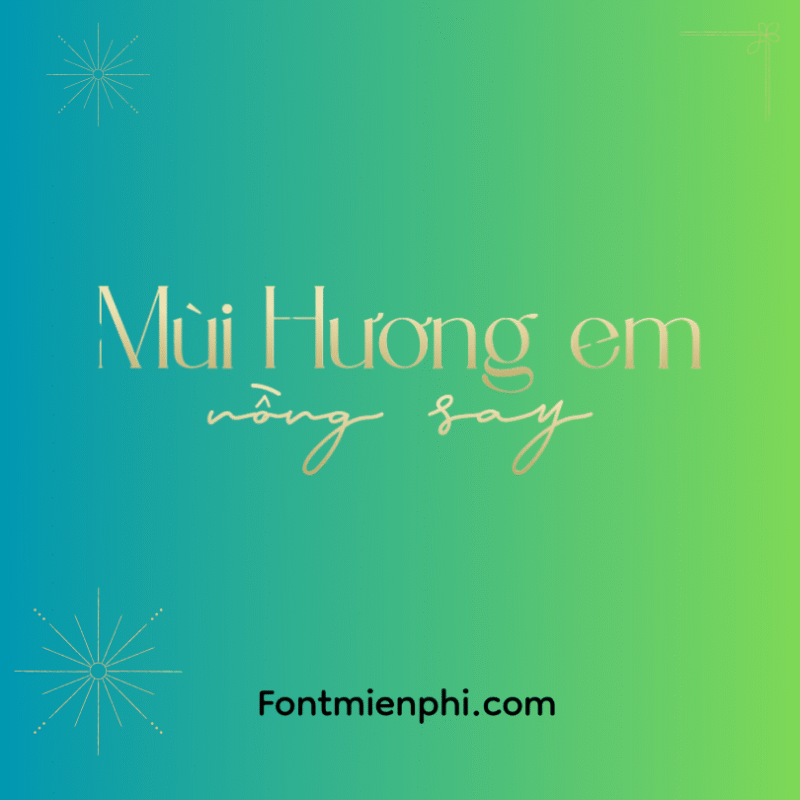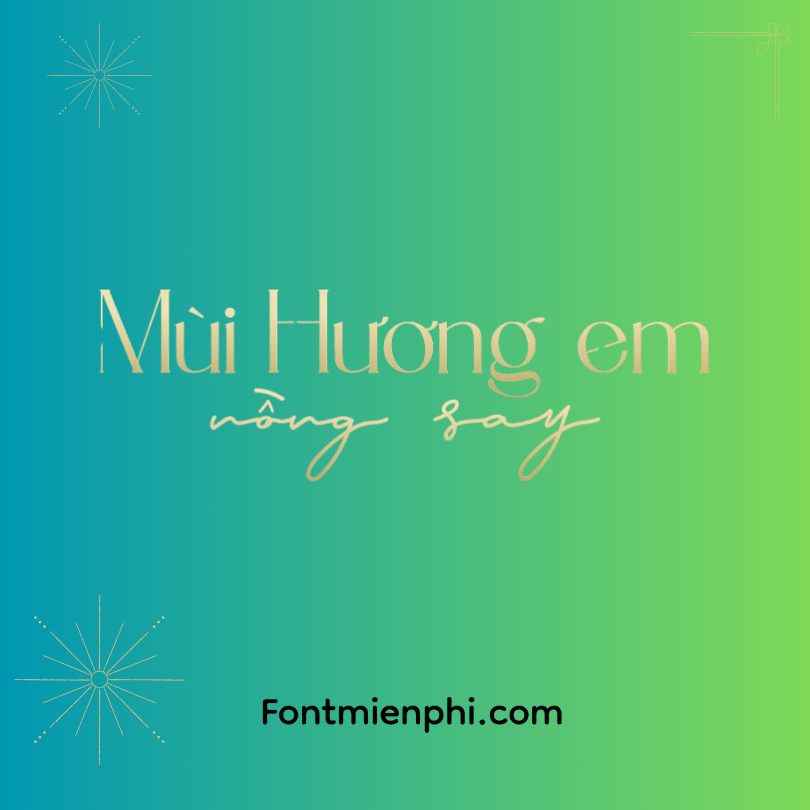
Font Việt hóa 1FTV VIP Borish , Font bất động sản, font spa thẩm mỹ
Font Việt Hóa 1FTV VIP Borish – Phong Cách Sang Trọng, Đẳng Cấp
Font 1FTV VIP Borish là bộ font chữ Việt hóa cao cấp, mang phong cách hiện đại, thanh lịch, phù hợp với các ngành bất động sản, spa, thẩm mỹ, thời trang và thiết kế sang trọng. Với nét chữ tinh tế, độc đáo, font Borish giúp tạo điểm nhấn cho logo, banner, namecard và các ấn phẩm marketing cao cấp.
Đặc điểm nổi bật:
✔ Hỗ trợ đầy đủ Tiếng Việt (TV) – Đảm bảo đọc rõ ràng, mượt mà.
✔ Đa dạng kiểu chữ – Bold, Italic, Regular phù hợp nhiều mục đích thiết kế.
✔ Phù hợp ngành bất động sản, spa, thẩm mỹ – Chuyên nghiệp, sang trọng.